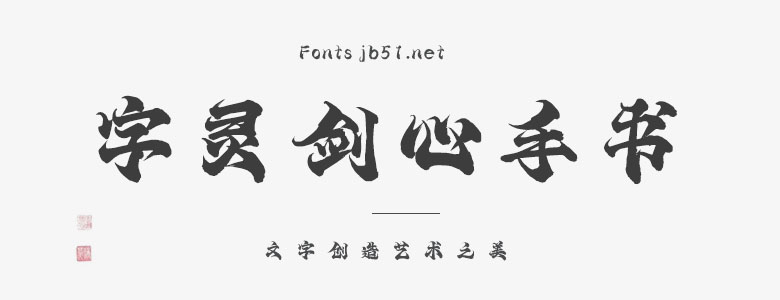
字靈劍心手書(shū)更大程度保留毛筆筆觸,更多細(xì)節(jié)展示字體邊緣,點(diǎn)、橫、豎、撇、捺,不同的位置,帶來(lái)不同的變化,適合應(yīng)用于藝術(shù)設(shè)計(jì)、平面宣傳設(shè)計(jì)、網(wǎng)頁(yè)設(shè)計(jì)、書(shū)法字體,海報(bào)設(shè)計(jì)等領(lǐng)域,歡迎喜歡這款字體的朋友下載收藏。